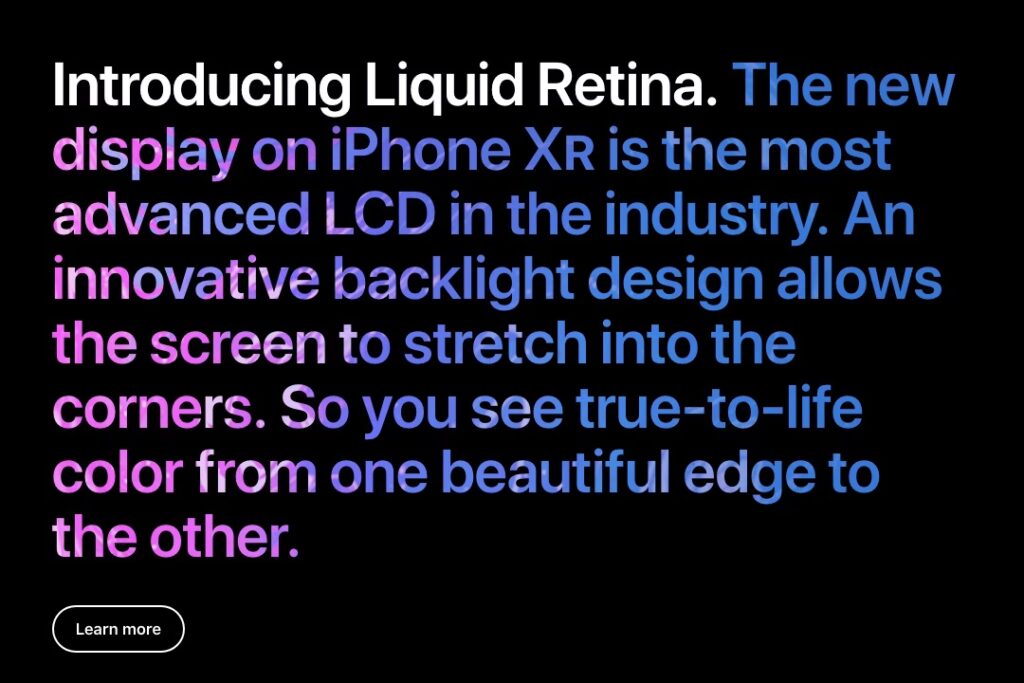
SF Font: Den Ultimative Guide til iOS Typografi
Når du designer en app til iPhone eller iPad, er valget af typografi afgørende for brugeroplevelsen. Apple har sine egne retningslinjer for fontstørrelser og -typer, som sikrer et ensartet og professionelt udseende på tværs af platformen. Denne guide dykker ned i de officielle iOS App Font Size Guidelines, med særligt fokus på SF Pro og SF Pro Display, den standard skrifttype, der definerer det karakteristiske iOS-look.
Hvad er SF Font?
SF, eller San Francisco, er Apples officielle systemskrifttype. Den er designet specifikt til at fungere optimalt på Apples enheder og giver en ren, læsbar og moderne æstetik. San Francisco-familien består primært af to varianter: SF Pro Display og SF Pro Text. SF Pro Display anbefales til større skriftstørrelser (20pt og derover), mens SF Pro Text er optimeret til mindre brødtekster og detaljer (19pt og derunder). At bruge disse skrifttyper er ikke et absolut krav, men det er den mest effektive måde at opnå det autentiske iOS-design på.
iOS Typografi Retningslinjer: En Oversigt
Apples retningslinjer for typografi er omhyggeligt udarbejdet for at sikre klarhed og konsistens. Lad os se på de mest almindelige elementer og deres anbefalede størrelser:
Titler (Sider eller Modaler)
Titler på sider eller i modaler er typisk de største teksttyper, du vil se. De bruger en Medium fontvægt for at skille sig ud. Før scrolling er titler ofte sat til 34pt. Når brugeren begynder at scrolle, skrumper titlen typisk ned til 17pt, hvilket er standardstørrelsen for mange andre elementer.
Brødtekst og Links
Standard brødtekst og links bør generelt være sat til 17pt. Dette giver en god læsbarhed på tværs af forskellige iPhone-modeller.
Sekundær Tekst
Til sekundær information, som f.eks. en e-mail-preview eller en beskrivelse, anbefales en størrelse på 15pt. Ofte bruges en lettere farve til at differentiere denne tekst fra den primære brødtekst.
Tertiær Tekst, Underskrifter og Segmenterede Knapper
For mindre elementer som tredjegrads tekst, underskrifter eller labels på segmenterede knapper, foreslås en størrelse på 13pt. Det er en god praksis at have en forskel i skriftstørrelse mellem sekundær og tertiær tekst for at skabe visuel hierarki.
Form Kontroller (Knapper, Tekstfelter)
Formularfelter som knapper og tekstinputfelter bruger ofte 17pt skrift. Det er vigtigt at fremhæve vigtige knapper eller aktive segmenter i segmenterede knapper med en Medium fontvægt.
Tab Bar
Teksten i tab-baren nederst på skærmen er typisk den mindste. Den anbefalede størrelse er 10pt. Det frarådes generelt at gå under denne størrelse for at opretholde læsbarhed.
Visuel Reference og Dybdegående Forklaring
Lad os se nærmere på, hvordan disse størrelser anvendes i praksis:
Titler og Skrolling
Forestil dig en app som Mail. Titlen på indbakken kan være imponerende stor (34pt) i starten. Men i takt med at du scroller ned gennem dine e-mails, skrumper titlen til en mere beskeden 17pt. Selvom størrelsen ændrer sig, bevarer titlen sin identitet som titel gennem dens placering (typisk øverst og centreret) og en tungere fontvægt. Dette er en subtil, men effektiv måde at guide brugerens opmærksomhed på.
Listevisninger
Lister er rygraden i mange mobilapps. I en e-mail-liste kan afsenderens navn være sat til standard 17pt, mens emnet og en kort preview-tekst kan være i 15pt. Dette kan virke kontraintuitivt, da man måske ville forvente, at afsenderen fremhæves yderligere. Men Apples filosofi her er at skabe et balanceret hierarki, hvor den primære information (emne og preview) kan have en lidt mindre, men stadig tydelig, størrelse.
På indstillingssider kan sektionstitler som "Systemlyd & Haptik" være mindre (f.eks. 13pt og i versaler) end de enkelte indstillingsmuligheder (17pt). Dette viser, hvordan kapitalisering og fontvægt kan bruges til at skabe visuelt hierarki, selv med mindre skriftstørrelser.
Form Kontroller i Detaljer
Når vi ser på segmenterede knapper, kan disse nogle gange have tekst på 13pt, selvom andre kontroller bruger 17pt. Dette skyldes sandsynligvis, at segmenterede knapper kan have mange muligheder, og en mindre skriftstørrelse hjælper med at passe teksten uden at kræve for meget plads.
Søgefelter bruger standardstørrelsen og vægten, men farven kan være lysere, før brugeren begynder at skrive. Dette indikerer, at feltet er aktivt, men endnu ikke udfyldt.
Modaler og Deres Typografi
Modaler, eller pop-up-vinduer, er illustrative eksempler på Apples typografiske tilgang. Titlen i en modal kan være i standard 17pt, men for at give den vægt, bruges en federe fontvægt. Den ledsagende forklarende tekst kan være 13pt, hvilket er mindre end de 15pt, der bruges i e-mail-previews. Dette kan skyldes et ønske om at holde teksten på en enkelt linje.
Inputfelter til adgangskoder bruger 17pt, som forventet. Knapper som "OK" og "Annuller" bruger også standardstørrelsen, men "OK"-knappen kan have en federe vægt for at signalere dens vigtighed som den primære handling.
Skal jeg bekymre mig om karakterafstand?
Hvis du sigter efter det præcise "standard iOS"-look, kan du overveje Apples anbefalinger for karakterafstand. Men for de fleste apps er systemets standardjusteringer tilstrækkelige.